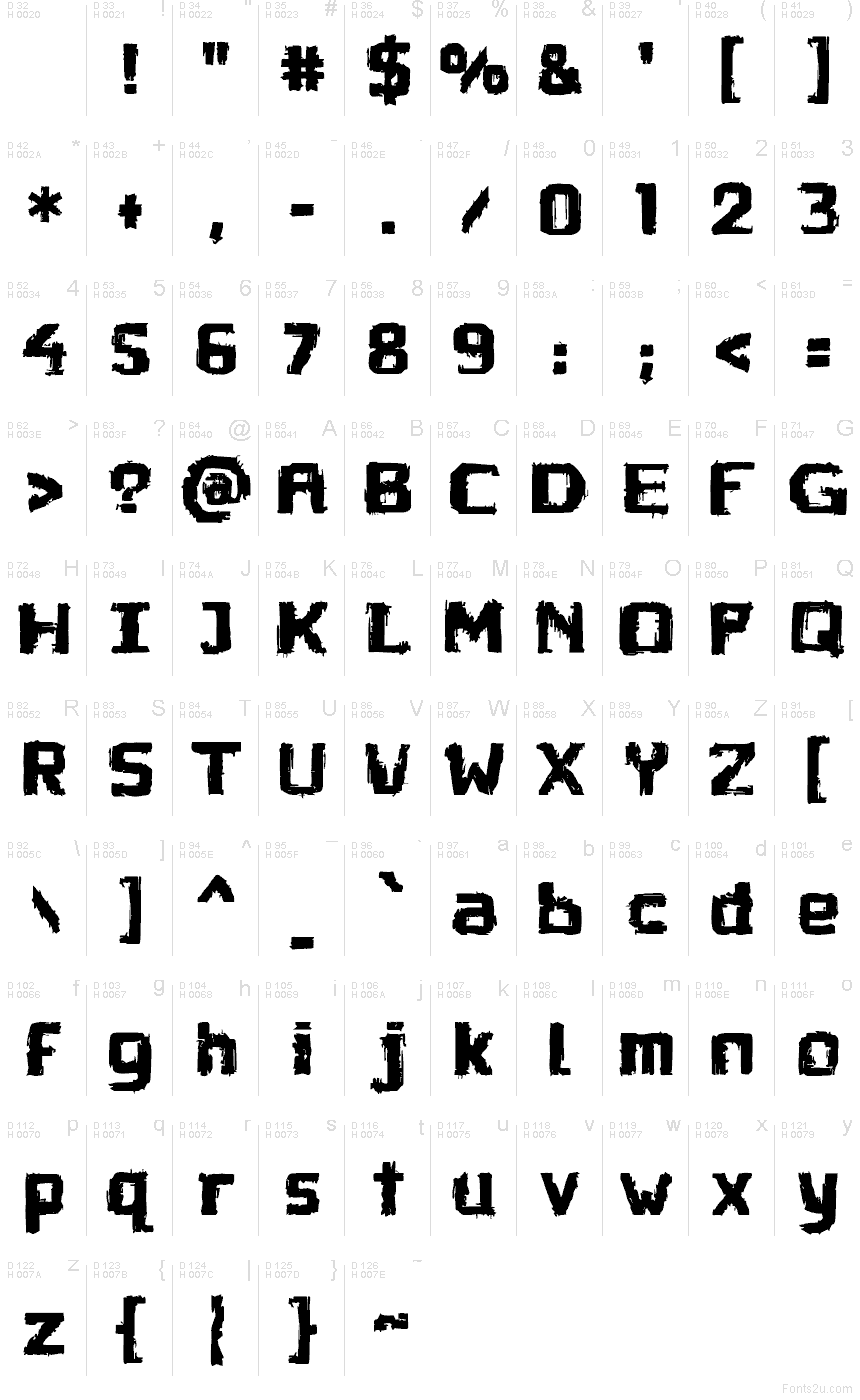
Zai Greenwashing Glitch est une police display gratuite au style glitch érodé, avec une allure brutalisée et fragmentée. Les lettres semblent griffées et interrompues ; avec ses formes massives, ses bords déchirés et ses petites ruptures, la police donne l'impression d'une signalétique endommagée par un bug numérique.
Elle est idéale pour les affiches, les pochettes d'album, les graphismes engagés, les couvertures de fanzines et les cartons de titre, là où cette texture usée et inquiétante peut porter le concept. Étant une police gratuite, elle convient aussi parfaitement aux titres courts et aux logos graphiques, car ses formes épaisses conservent tout leur caractère, même dans des textes brefs.